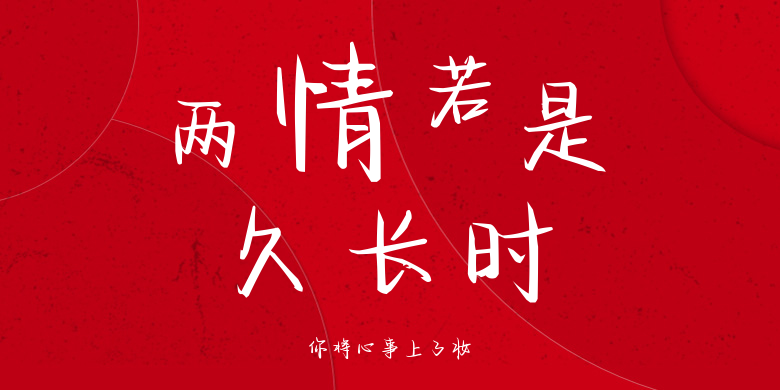
你将心事上了妆
你将心事上了妆,这款字体结构工整、笔画清晰,兼顾美观与易读性,适用于标题、正文、海报、包装、LOGO 等多种场景。字形优雅稳定,风格百搭耐看,适配日常排版与创意设计,让文字呈现更舒适、更具质感。你将心事上了妆一笔一画,皆是细节,以均衡的比例、流畅的线条打造舒适视觉体验,字形端正大气,风格简约现代。无论是商业设计、品牌宣传还是日常排版,都能轻松驾驭,让文字更有格调与力量。你将心事上了妆字体下载。